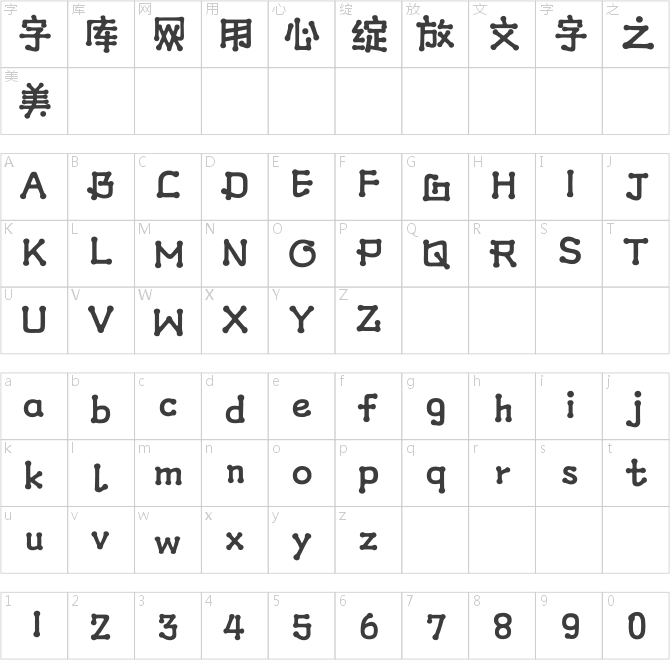
漢儀蜜糖體性格活潑可愛,像糖果一樣給人帶來甜蜜的感覺。這款字體的起筆收筆和轉(zhuǎn)折處都以圓潤為主,像棒棒糖一樣。字體結(jié)構(gòu)豐富多變,有著各式各樣的大小對比關(guān)系,為字體增添了更多趣味性。
漢儀蜜糖體 W字體HYMiTangTiW字庫是一款讓人賞心悅目、百看不厭的中文字體,適合各類廣告和產(chǎn)品包裝設(shè)計應用,字體大小11.73MB,格式為ttf字體,上傳用戶是喜歡戳爺,作者/版權(quán)方為漢儀字庫